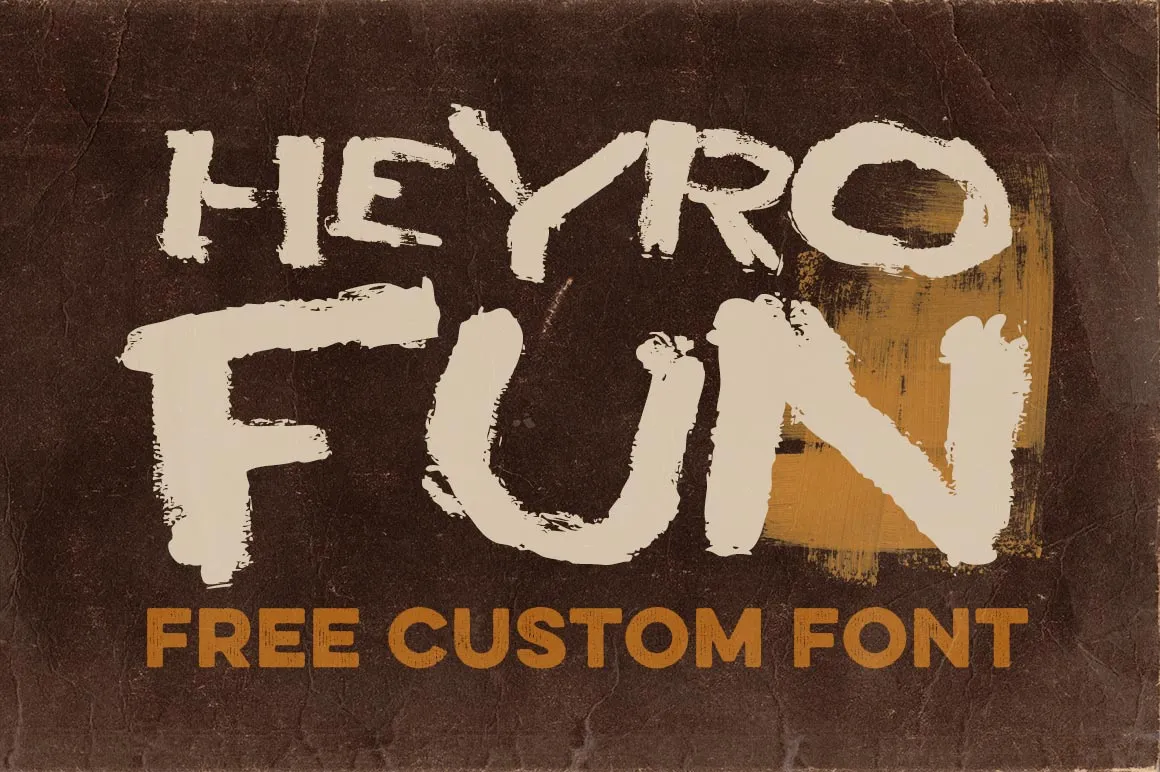
A fonte ‘HEYRO Fun Font’, criada pelo designer Hamilton, é perfeita para quem busca um estilo alegre e descolado. Esta font tem uma vibe criativa e grunge que se sobressai, fornecendo um toque único aos seus projetos. Ideal tanto para nomes de marca quanto para design gráfico, ela enriquece suas criações com uma pitada divertida e atemporal. Se você está à procura de algo diferente, mas ainda bem feito, esta font é perfeita para aprimorar seu trabalho em progresso. Descarregue-a agora e divirta-se explorando seus recursos inusitados.